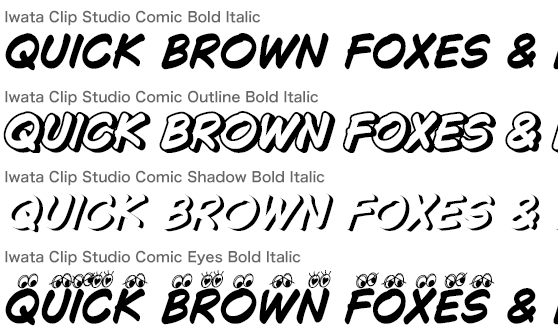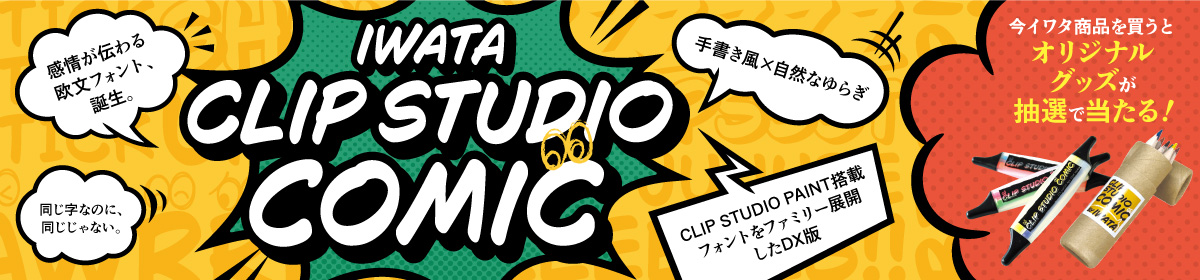
欧文手書き
Iwata Clip Studio Comic Bold Italic 4書体セット (Bold Italic/Outline Bold Italic/Shadow Bold Italic/Eyes Bold Italic)
株式会社イワタが株式会社セルシスと共同で開発し、イラスト・マンガ・Webtoon・アニメーション制作ソフト「CLI P STUDIO PAINT」に搭載されている欧文フォント「Clip Studio Comic」のイワタDX版。標準的な文字の他に縁取りした「Outline」、影のみの「Shadow」、文字の上にかわいらしい目を追加した「Eyes」4書体の Bold Italic セット。
よりリアルな手書き感を表現するために、1つの文字に複数のデザインを用意し、それらをランダムで表示させる処理も実装し、手書き文字ならではの揺らぎ再現しています。